비전공자들을 위한 타이포그래피
타이포그래피 :
글자를 또렷하고 읽기 쉽고
매력적으로 보이기 위해
활자를 배열하는 예술, 혹은 기술
타이포그래피는 디자이너들에게 있어 가장 기본이면서도 필수 요소지만, 디자이너가 아닌 일반인들에게는 다소 생소할 수 있는 용어입니다. 하지만 우리가 단지 인지하지 못할 뿐, 타이포그래피는 책, 광고, 가게 간판, 심지어 휴대폰 화면까지 우리 일상 어느 곳에나 존재하고 있습니다.
이번 글에서는 타이포그래피가 익숙하지 않은 일반인들을 위해 좋은 타이포그래피를 쉽고, 빠르게 구축할 수 있는 방법들을 소개해 보려고 합니다.
1. 알맞은 폰트 사용하기
고딕과 명조, 두 가지로 구분되는 국문 폰트와 다르게 영문 폰트는 세리프와 산세리프 안에서도 나눠지는 많은 스타일이 있습니다. 영문 폰트의 역사에서 각 스타일은 특정한 목적을 위해 탄생한 경우가 많기 때문에, 이 점을 이해하고 사용하면 디자인의 전반적인 인상을 쉽게 바꿀 수 있고, 가독성을 크게 개선할 수 있습니다.
영문 폰트에서 각 스타일의 특징들과 활용 방법 더 알아보기
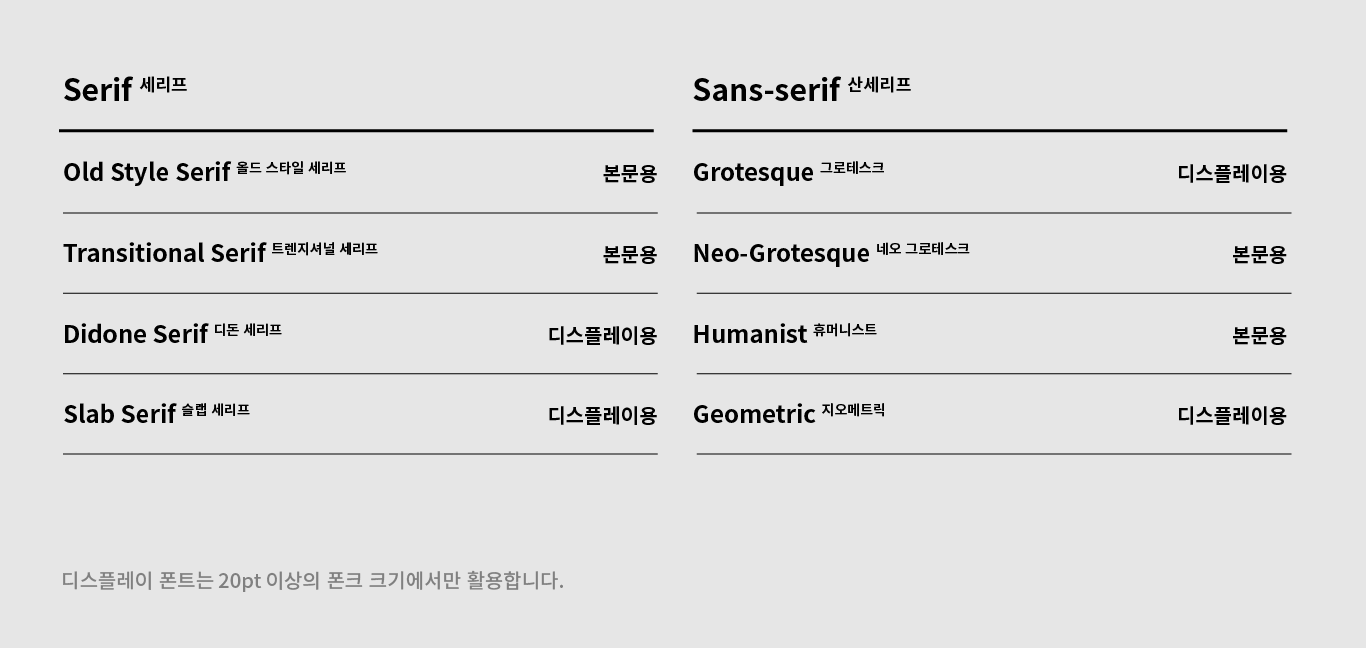
+ 디스플레이용 폰트 (Display Font) vs. 본문용 폰트(Text Font)
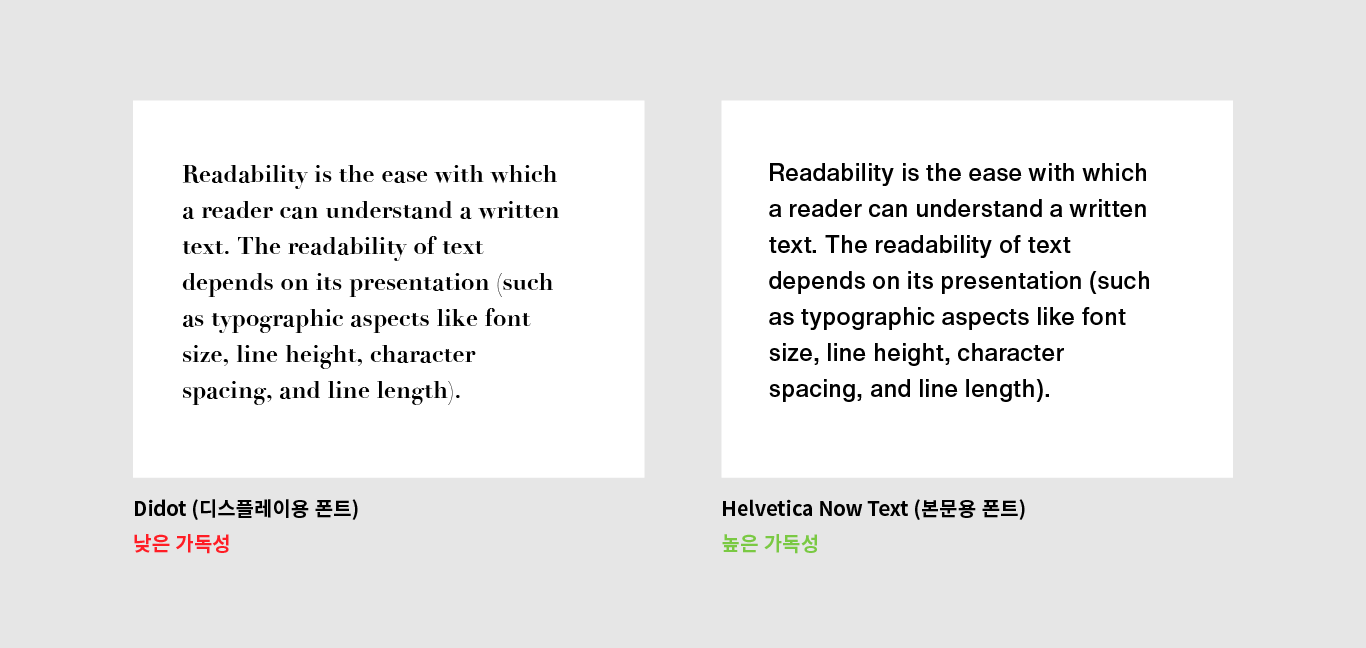
디스플레이 폰트는 가독성보다는 간판, 타이틀에서 이목을 끌기 위해 제작된 폰트이므로 본문용으로 사용하는 일은 반드시 피해야 합니다.
2. 자간
폰트의 크기가 커질수록 글자 사이의 공간 또한 넓어지기 때문에 자간이 조정되어야 합니다. 일반적으로 본문용 폰트는 자간이 넓게 세팅되어 있어 20pt가 넘어가면 자간을 줄여야 텍스트의 가독성을 높일 수 있습니다. 국문 또한 같은 방식으로 자간을 조정합니다.
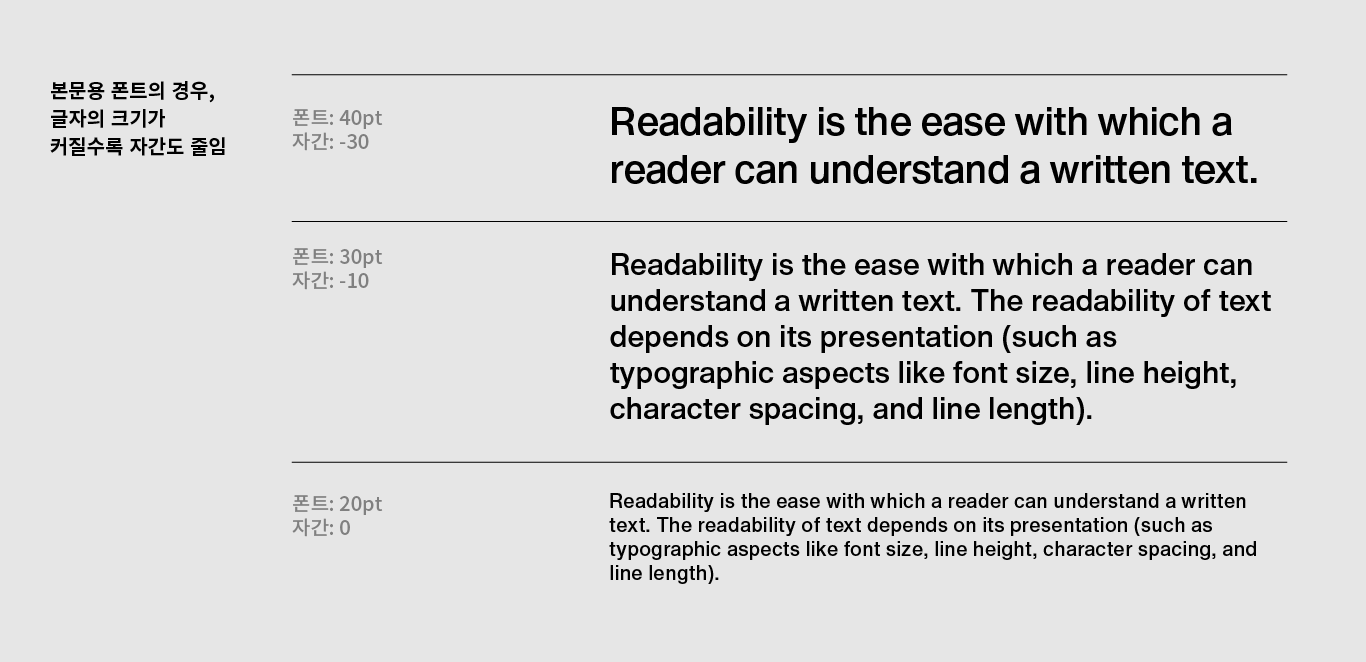
3. 행간
행간은 가독성에 있어 가장 큰 부분을 차지하는 요소 중 하나입니다. 행간이 너무 좁으면 눈에 피로를 줄 수 있고, 반대로 너무 넓으면 집중력을 저하시킬 수 있기 때문입니다. 행간은 글줄 길이에도 영향을 받기 때문에, Set Solid(행간 = 폰트 크기)와 Double Spacing (행간 = 폰트 크기 x2) 사이를 유지하며 적절한 행간 값을 찾는 것이 중요합니다. (국문은 영문과 달리 모든 글자들이 비슷한 폭을 가지고 있으며, 세로로도 읽힐 수 있기 때문에, 항상 충분한 행간 값을 주어야 합니다.)
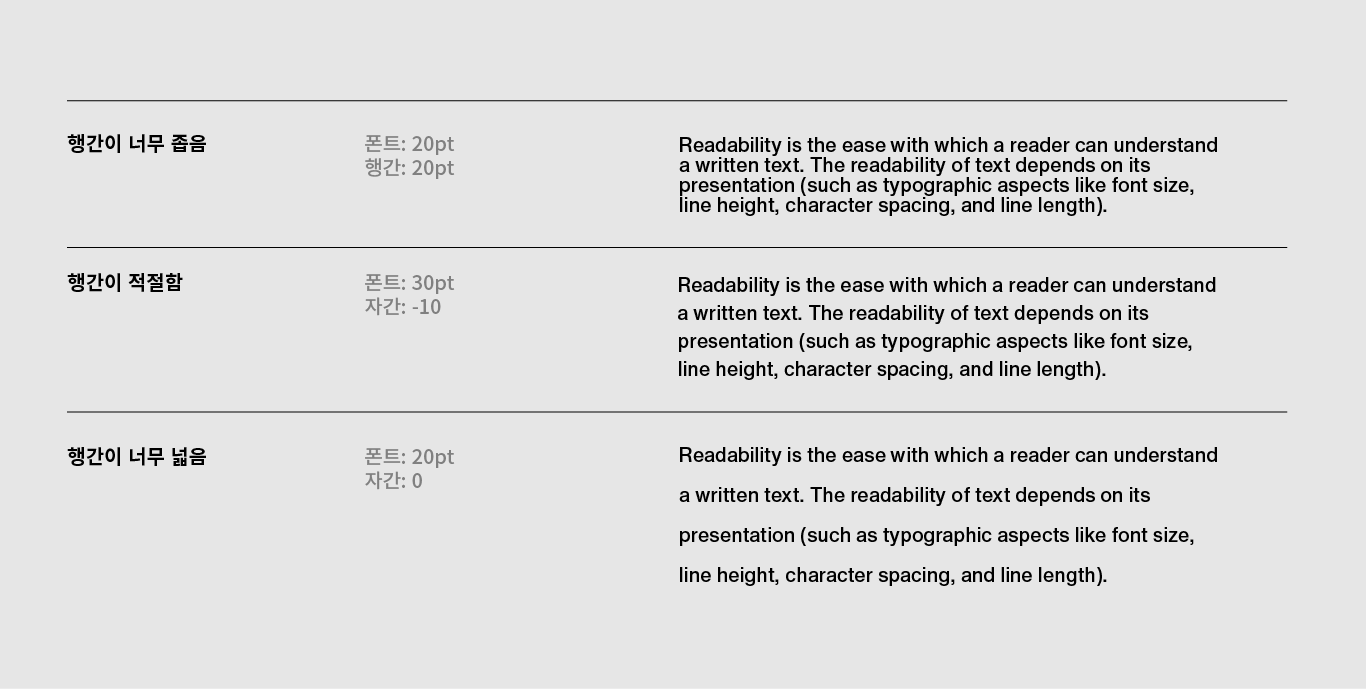
4. 글줄 길이
글줄 길이는 자간과 행간과 더불어 가독성에 큰 영향을 끼치는 요소 중 하나입니다. 웹사이트의 경우, 너무긴 글줄 길이는 사이트 이탈률의 원인이 됩니다. 텍스트는 한 줄에 글자 40에서 60자 사이를 유지하며 텍스트의 양이 많거나, 텍스트가 들어가는 공간의 좌우 폭이 너무 넓을 경우에는 다중 칼럼 (multi column)을 사용하시는 것을 권장합니다.
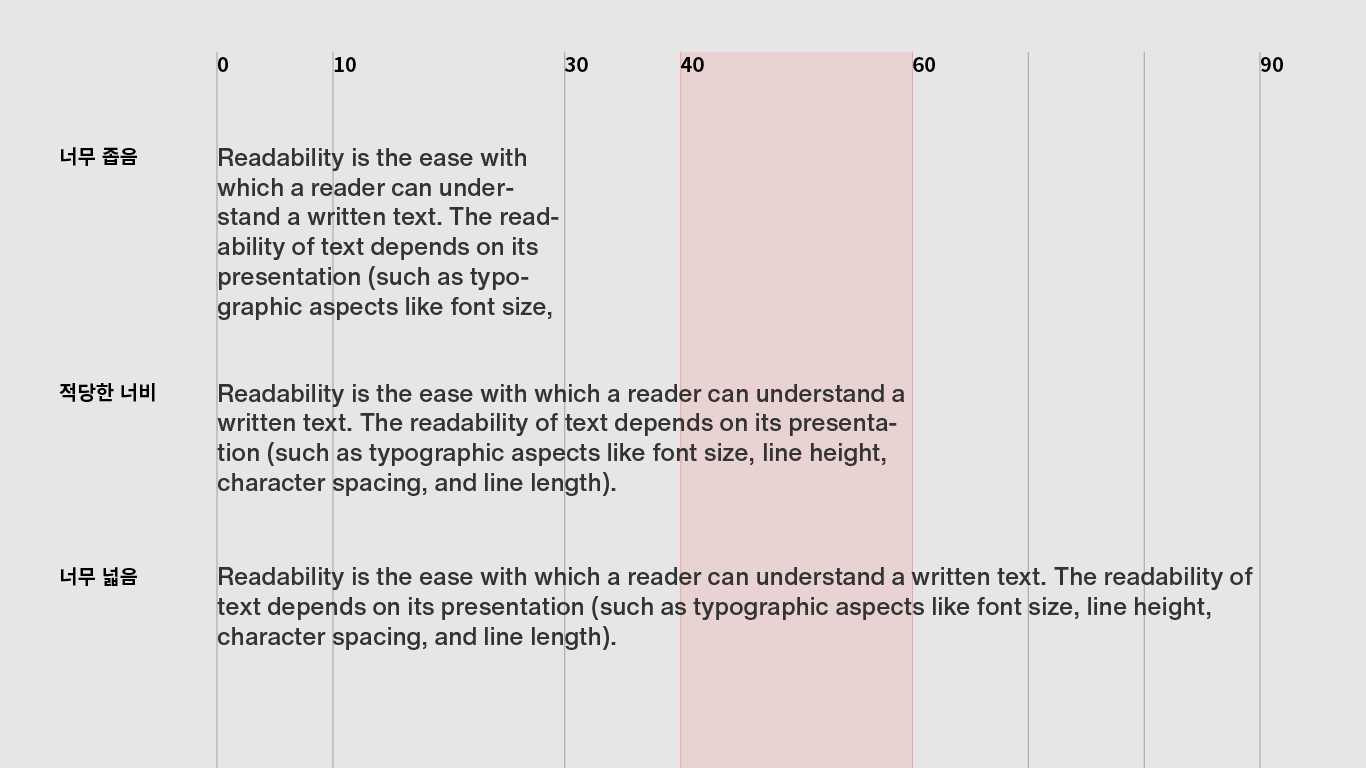
5. 정렬
영문과 국문은 좌측에서 우측으로 읽기 때문에 항상 좌측 정렬이 최우선 되어야 합니다. 특히 영문은 대문자와 소문자가 혼용되어 국문보다 여백이 많기 때문에 우측 정렬은 시각적인 안정성을 떨어뜨리고 가독성을 크게 저하시킬 수 있습니다. 따라서 중앙 정렬은 2-3 문장을 넘지 않은 단문에서만 사용하고 우측 정렬은 본문과 시각적으로 분리되어야 하는 caption과 같은 용도에서만 활용합니다.
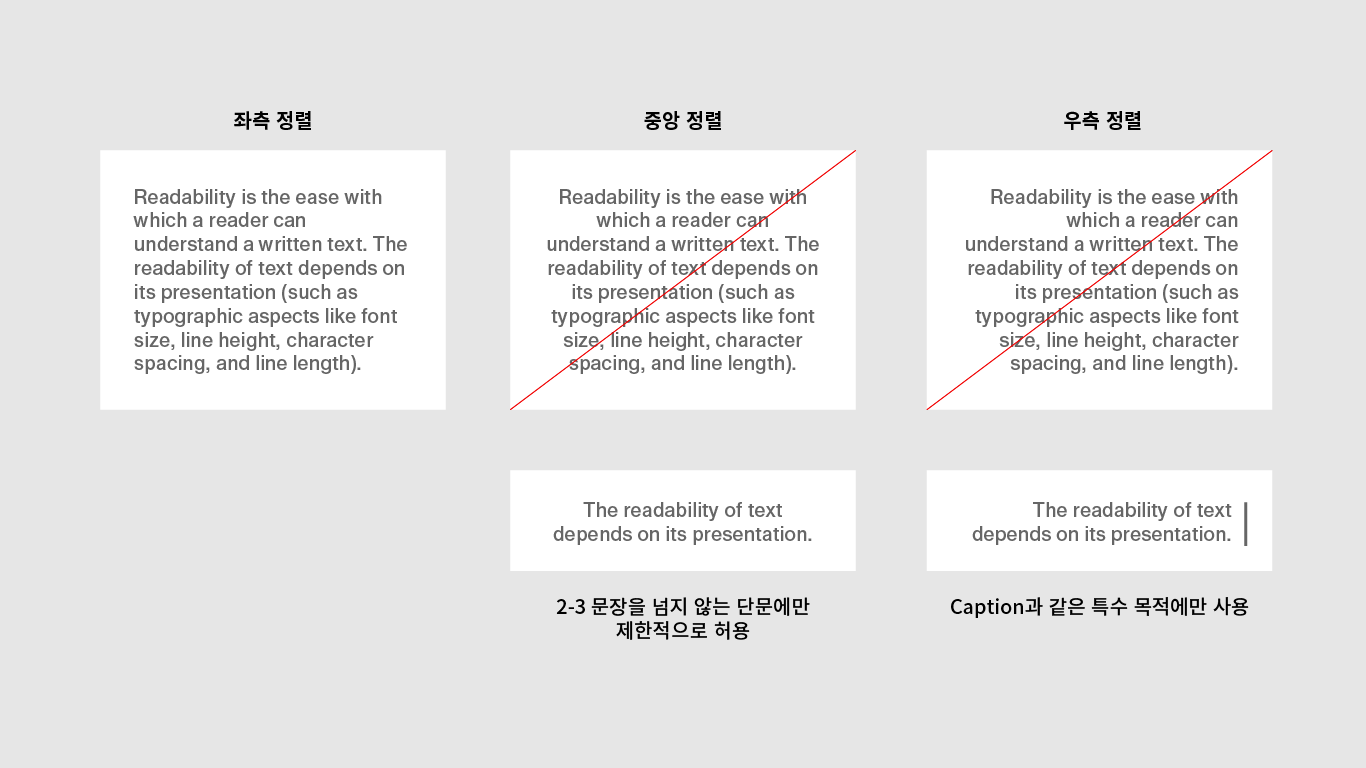
6. 배경색과 대비
배경과 폰트의 색상 또한 가독성의 큰 영향을 끼치는 요소 중 하나입니다.
어두운 배경에서 글자 획의 대비가 강한 폰트와 너무 얇은 두께의 폰트는 판독성(legibility)이 떨어짐으로 피하시는 게 좋으며, 또한 밝은 배경에 비해 글자의 간격이 좁아 보이는 착시현상을 줄 수 있음으로 자간을 살짝 넓게 조정하는 것이 좋습니다.
폰트와 배경 모두에 색상을 사용할 경우에는 Grayscale로 변환하여 테스트해보시는 것이 좋습니다. 명암 대비가 확실하지 않다면 웹 환경에서 접근성이 떨어질 수 있습니다.
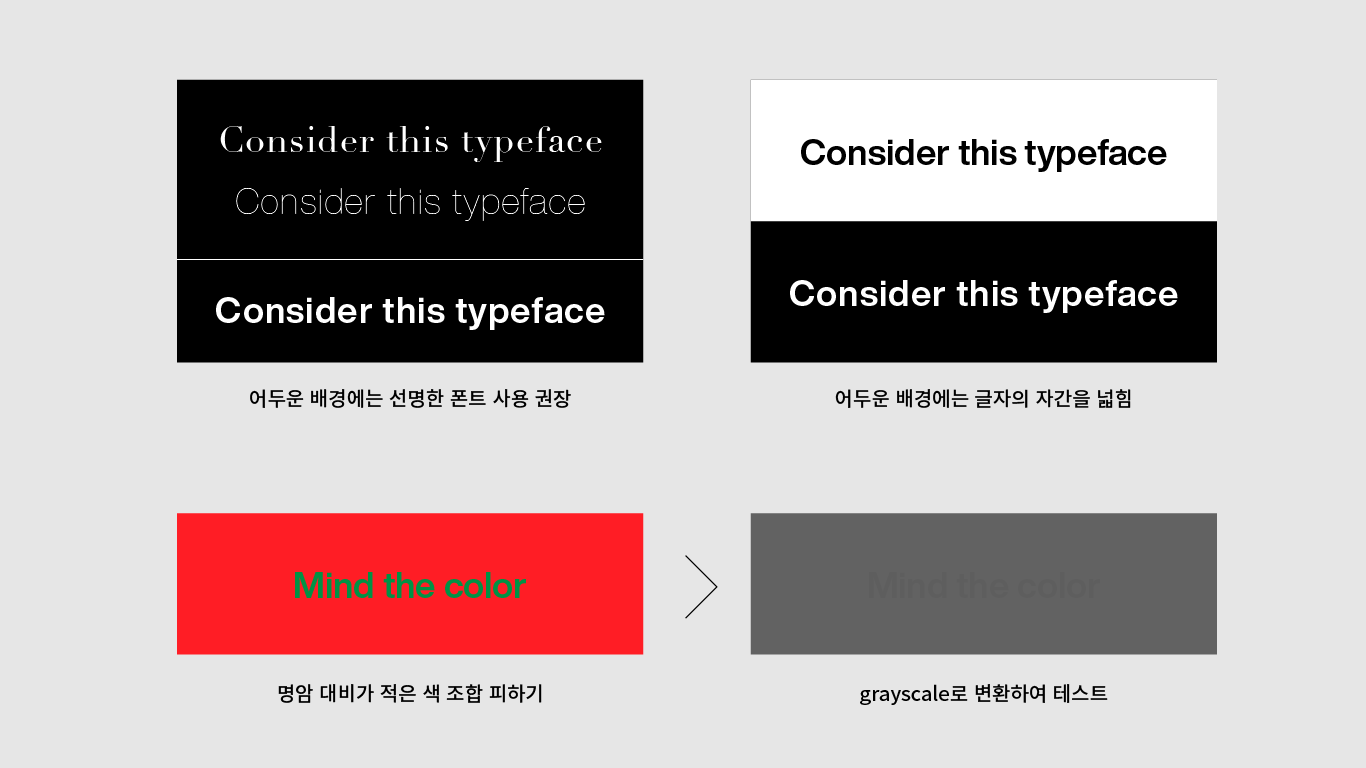
7. 이미지와 텍스트
디자인을 하다 보면 솔리드 배경이 아닌 이미지 위에 텍스트를 배치해야 하는 경우도 있습니다. 가장 좋은 방법은 텍스트를 배치할 만큼 충분한 여백이 있는 이미지를 고르는 것입니다. 하지만 불가피하게 복잡한 이미지를 사용하는 경우에는 아래의 방법을 통해 텍스트를 삽입할 수 있습니다.
- 이미지 일부에 솔리드 배경을 올려 텍스트의 가독성을 높임
- 이미지 일부에 그라디언트 배경을 삽입하여 텍스트와 이미지의 대비를 줌
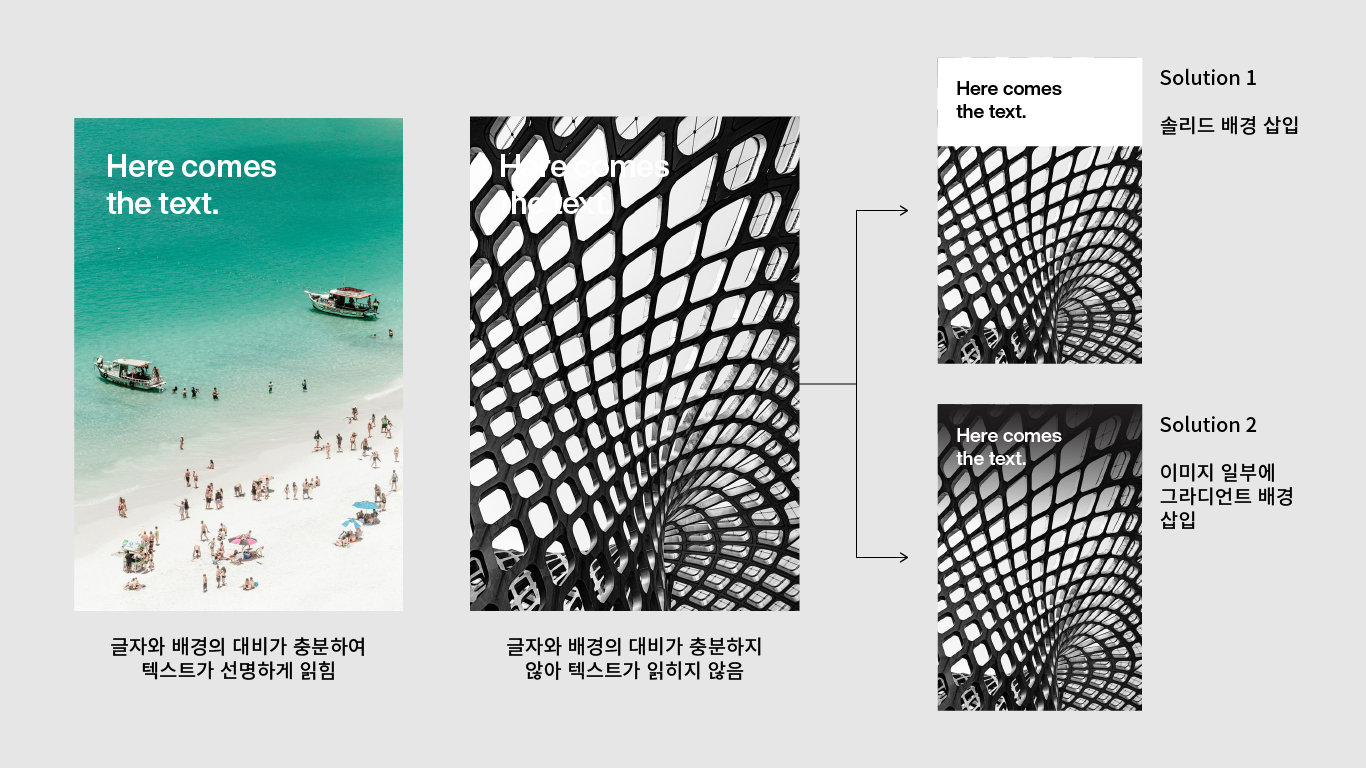
텍스트에 드롭 쉐도우 효과를 주거나, 아웃라인을 주는 것은 텍스트의 가독성을 떨어뜨리기 때문에 피하시는 것이 좋습니다.
8. 폰트 변형하지 않기
많은 비전공자들이 한정된 공간에서 텍스트를 삽입할 때, 공간에 맞추기 위해 폰트를 압축하거나 늘이는 경우가 종종 있습니다. 이는 폰트 디자이너들이 폰트를 제작할 때 고려한, 미세한 획의 대비와 곡률 등 폰트의 디테일들을 손상시키는 행위이므로 단순히 공간에 끼워 맞추기 위해 폰트를 변형하는 일은 없어야 합니다.
최근에는 많은 폰트 제작사들이 폰트가 다양한 환경에서 사용될 수 있도록 Condensed, Wide와 같은 폰트들도 폰트 패밀리에 포함하고 있기 때문에 임의로 변형하지 않고도 상황에 맞는 폰트를 골라 사용할 수 있습니다.
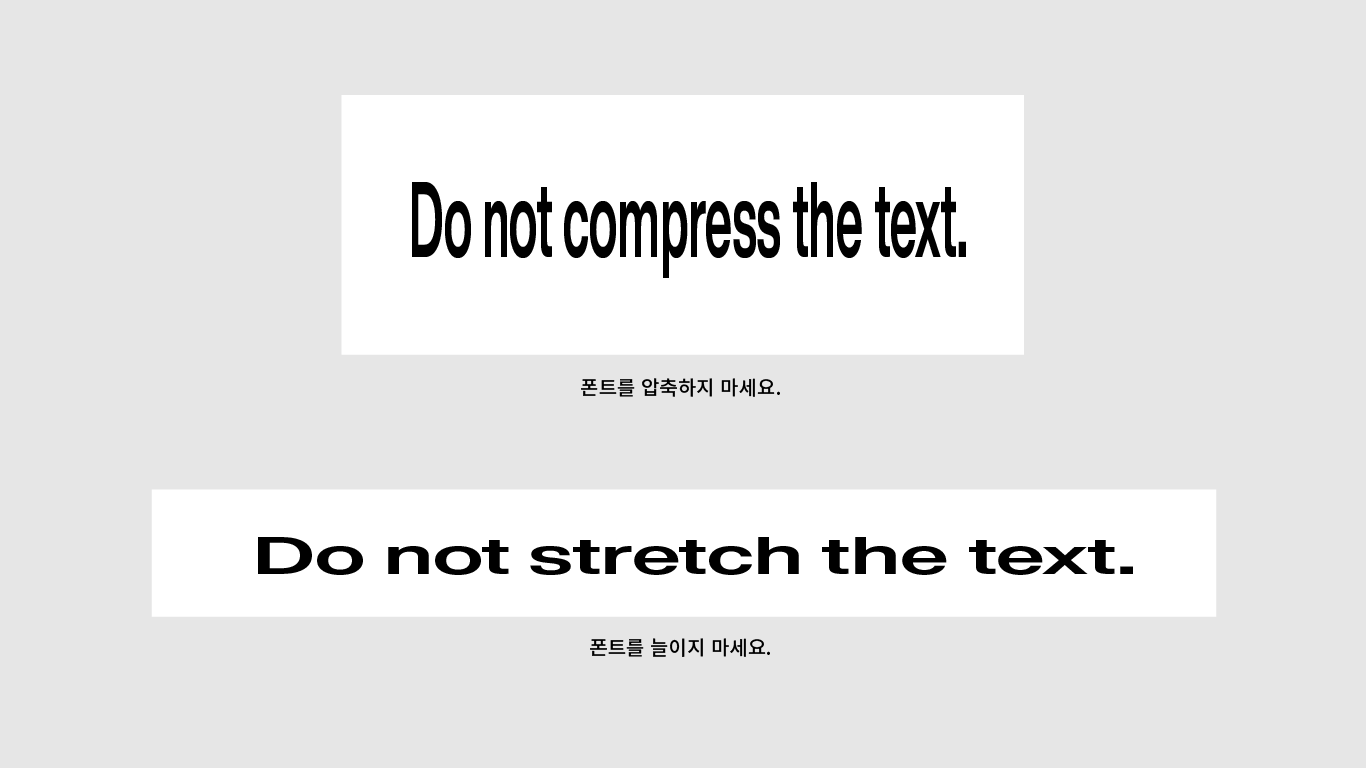
9. 가독성 테스트 하기
사실상 많은 훈련을 한 디자이너가 아니라면 해당 텍스트가 가독성이 좋은지 확인하기 어려울 수도 있습니다. 자간, 행간, 텍스트 크기, 색상 등 다양한 요인들이 합쳐져 가독성에 영향을 끼치기 때문입니다. 이를 테스트하는 가장 쉬운 방법은 눈을 찌푸려 텍스트를 보았을 때 텍스트가 배경과 좋은 대비를 이루는 회색이 되었는지를 보는 것입니다.
회색이 너무 희미하거나 얼룩덜룩할 경우에는 위에 언급한 요소들을 하나씩 체크해보는 것을 추천드립니다.